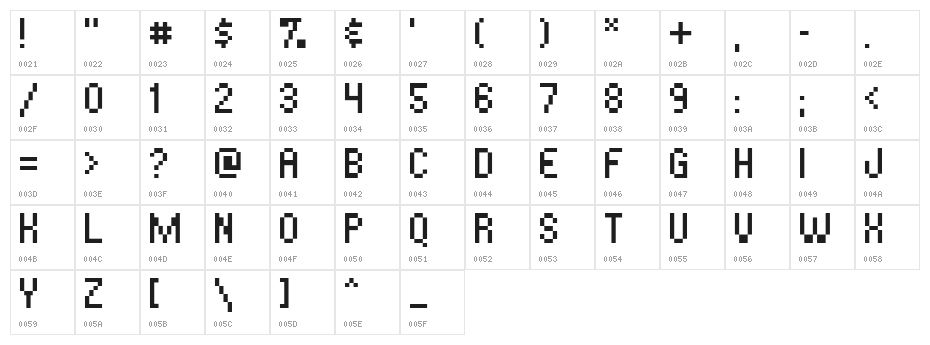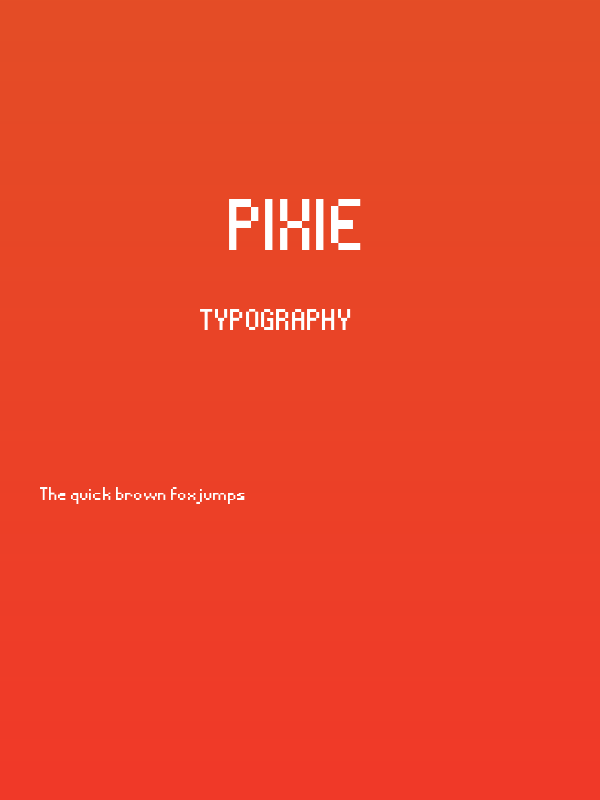
pixie Font
| Caz de utilizare | Headlines, Logos, Digital Art |
| Proiecte propuse | Ideal for retro video game designs, digital art projects, tech-themed posters, and any creative work that seeks a nostalgic or digital aesthetic. |